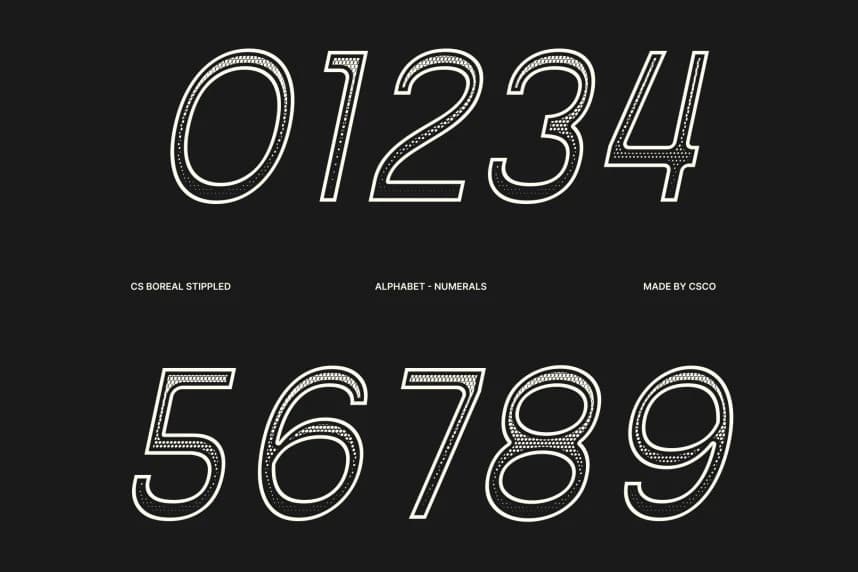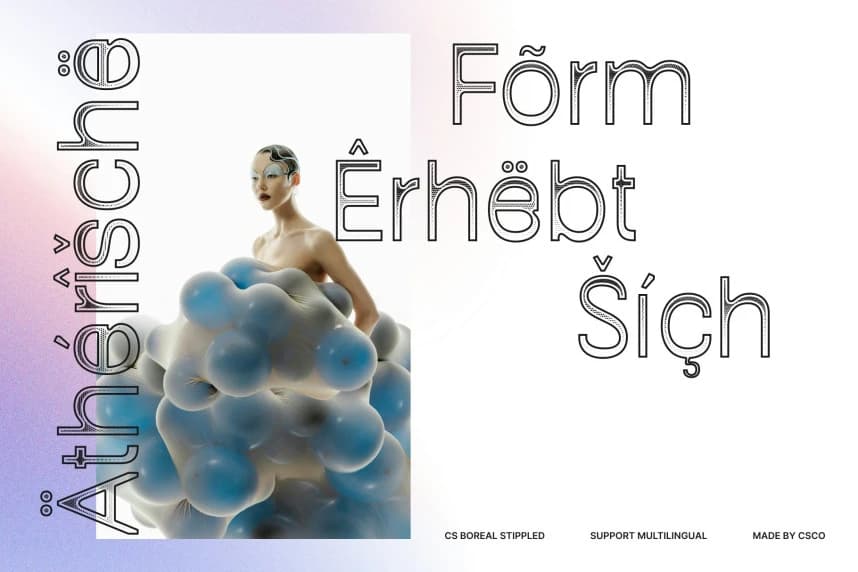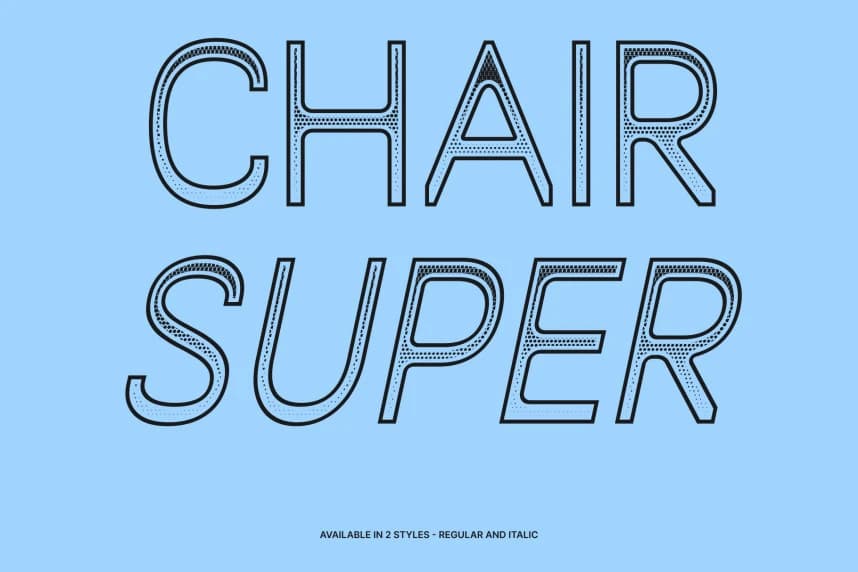
CS Boreal Stipleli Yazı Tipi
CS Boreal Stippled Font – Taze ve özgün karakterlere sahip modern Sans Serif fontu; temiz ve çağdaş Sans Serif fontu. Bu, temiz tasarımı tuhaf ve ayırt edici şekillerin birleşimini sunan modern bir Sans Serif fontudur.
CS Boreal Stippled Font – Taze, özgün karakterlerle modern sans serif. Bu, temiz bir yapıyı tuhaf, ayrıcalıklı şekillerle birleştiren çağdaş bir sans serif yazı tipidir.